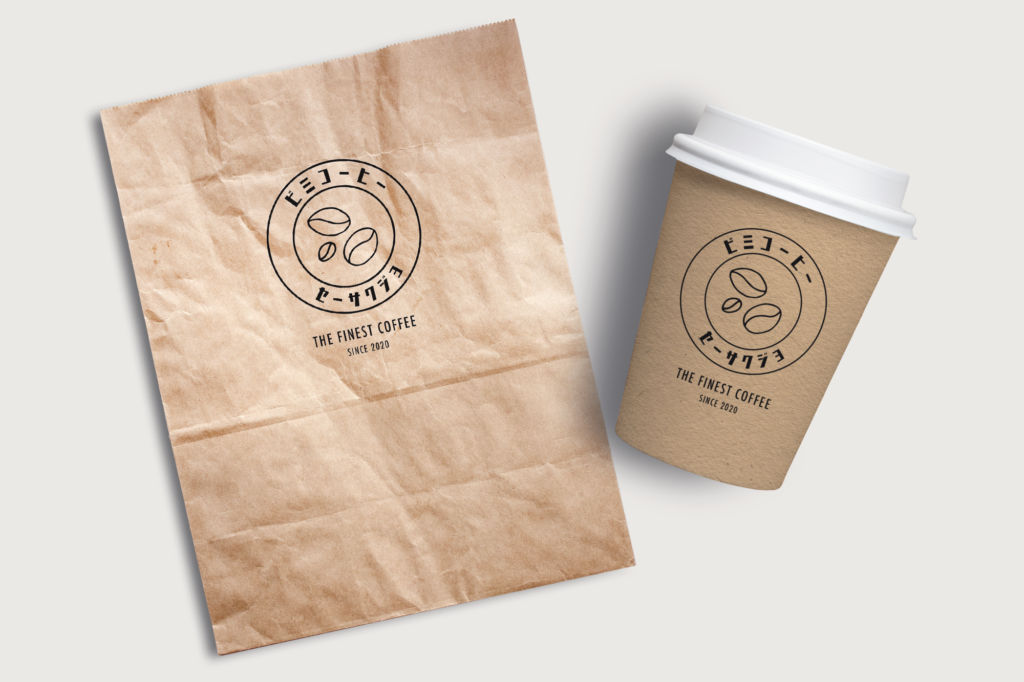
今回のバンドルは「テーマパークみたいな楽しい日本語フォント集」。漢字も使えるかわいくて実用的な丸ゴシックフォントや漫画の吹き出しなどに活躍するユニークなデザインフォントなど、8書体のディスプレイフォントと22書体のカナフォント、合計30書体を収録しています。
「テーマパークみたいな楽しい日本語フォント集」の気になる中身
漢字に対応したかわいくて実用的な丸ゴシックフォント
かわいいのに漢字も使えて読みやすい丸ゴシックフォントを4書体収録。ポスターやチラシ、本の表紙など幅広く利用できます。
- シーモオープンボールド
- シーモ太丸ゴシック
- まーとオープンボールド
- ルイ中細丸ゴシック
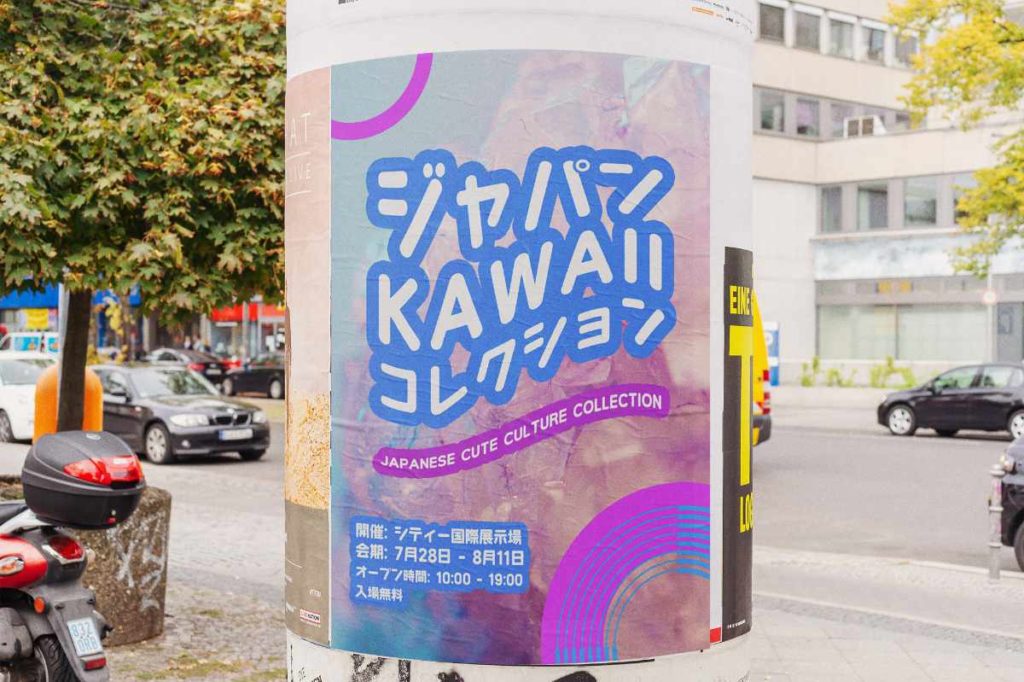
デザインにインパクトを与える書体集:C&G和風ディスプレイフォント
デザインに遊び心を加えられるC&G和風ディスプレイフォントはユニークな4書体を収録。C&G半古印はノスタルジックからオカルト系まで特に守備範囲の広いデザインフォントです。
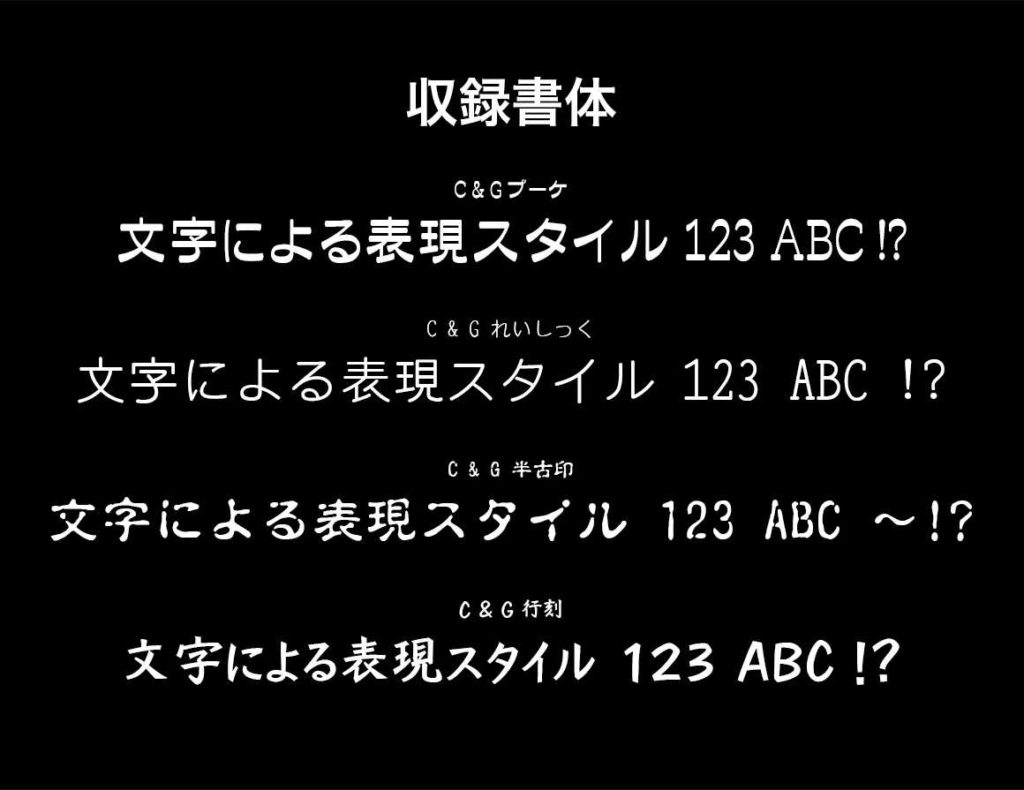
- C&Gブーケ
- C&Gれいしっく
- C&G半古印
- C&G行刻
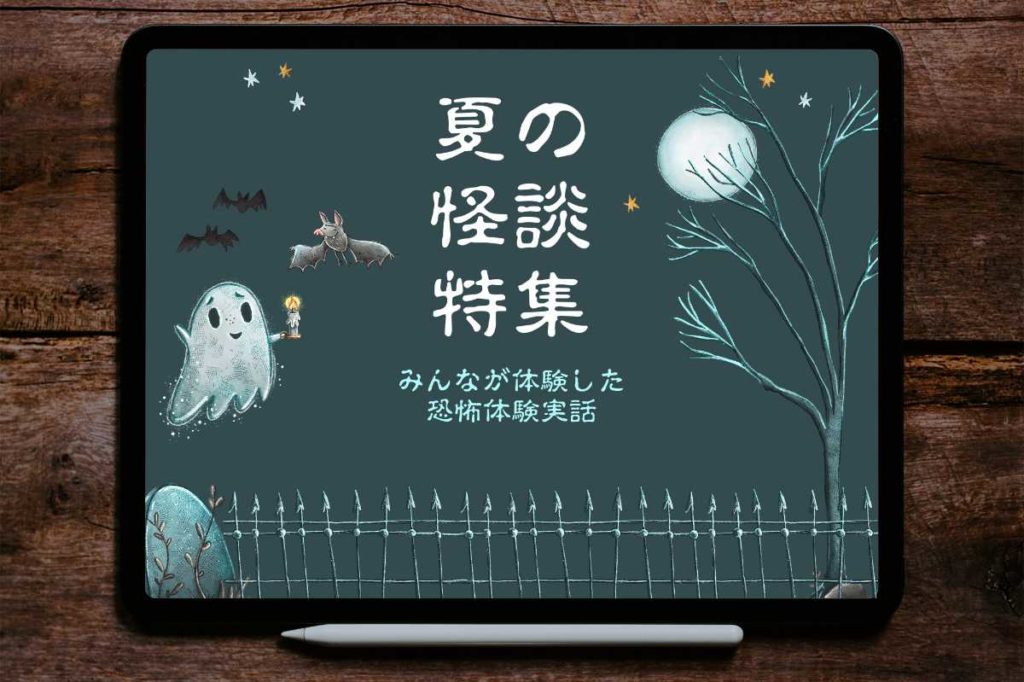
ロゴやラベルデザインも簡単!カナフェイス44
ロゴやラベルなどのデザインに大活躍する、様々なイメージでデザインされたカナフォントを22種類収録。漢字対応の他のフォントと組み合わせることもできます。
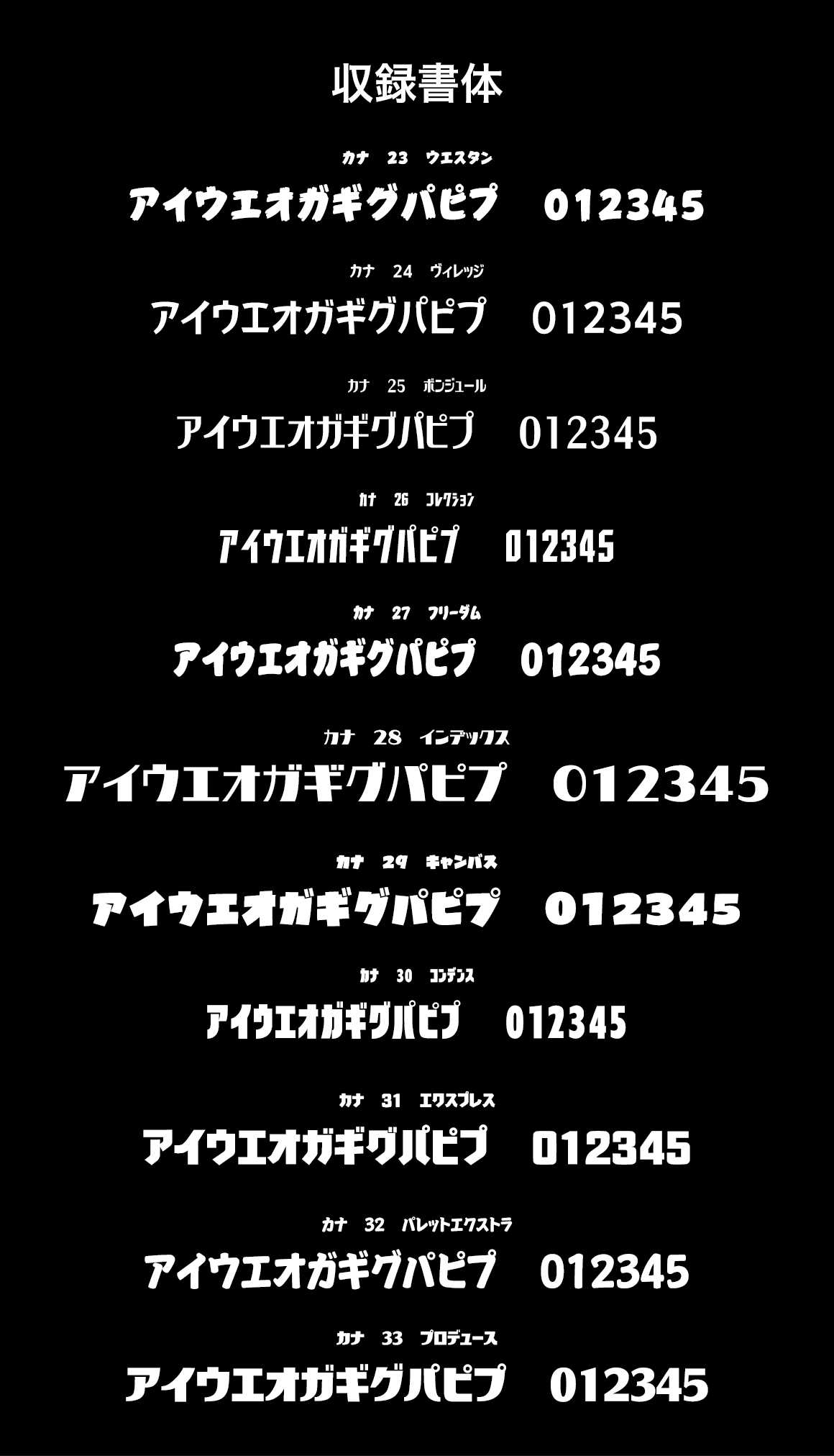
- カナ23ウエスタン
- カナ24ヴィレッジ
- カナ25ボンジュール
- カナ26コレクション
- カナ27フリーダム
- カナ28インデックス
- カナ29キャンバス
- カナ30コンデンス
- カナ31エクスプレス
- カナ32パレットエクストラ
- カナ33プロデュース
- カナ34ビッグボックス
- カナ35シルバーベル
- カナ36ルーレット
- カナ37カシオペア
- カナ38オーディション
- カナ39スタジアム
- カナ40ウェーブ
- カナ41パーカッション
- カナ42プロムナード
- カナ43フルハウス
- カナ44キューブ